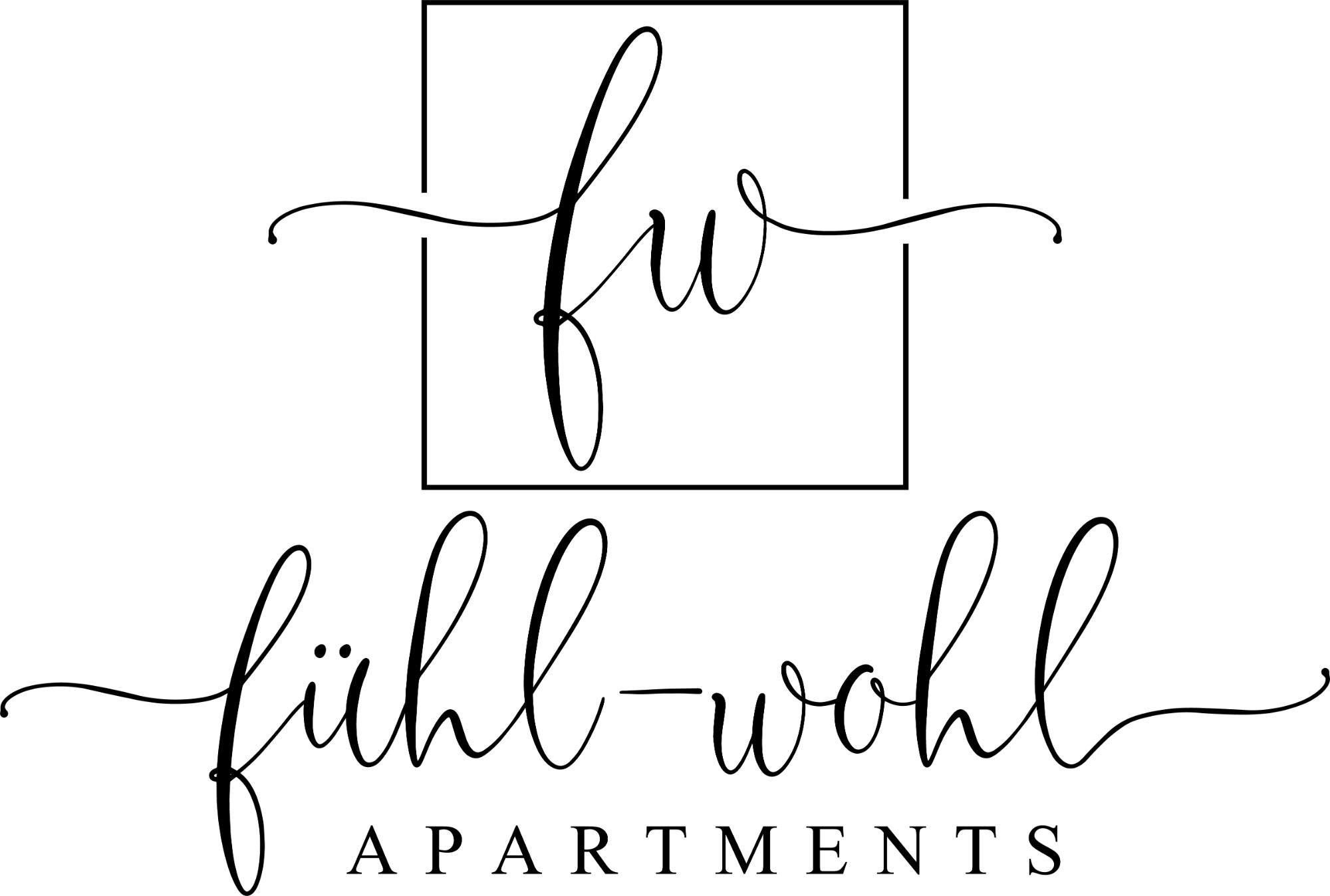
Schriftarten aus Fiverr-Logo gesucht
ich suche die Schriftarten aus dem Logo. Dieses wurde Anfang des Jahres bei Fiver erstellt und der Designer ist inzwischen nicht mehr verfügbar.
Erkennt jemand von euch, welche Handwriting und serifenbetonte Schriftart das jeweils ist?
Hihi, ich verstehe was du meinst mit dem "l-Schwanzerl". Vielen Dank für deine Meinung dazu. 🙏🏻